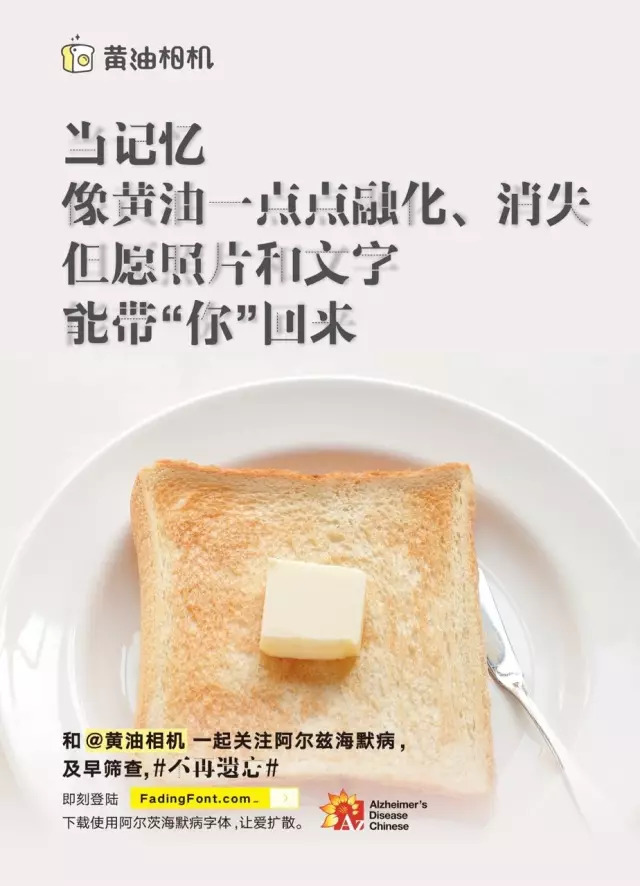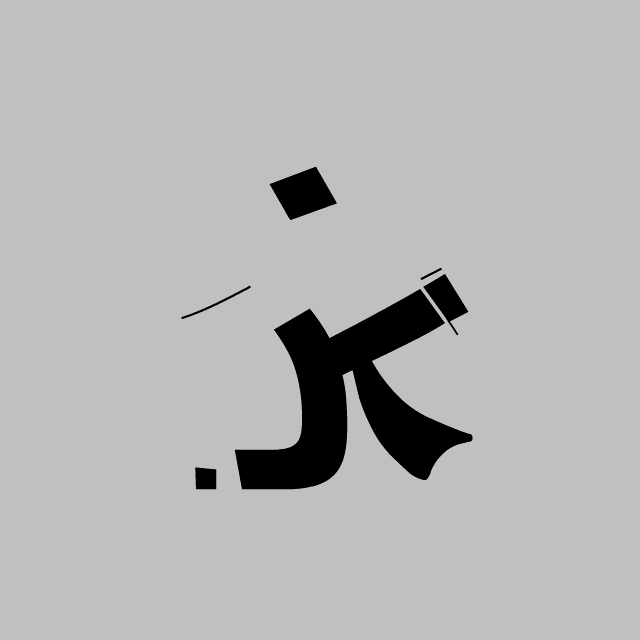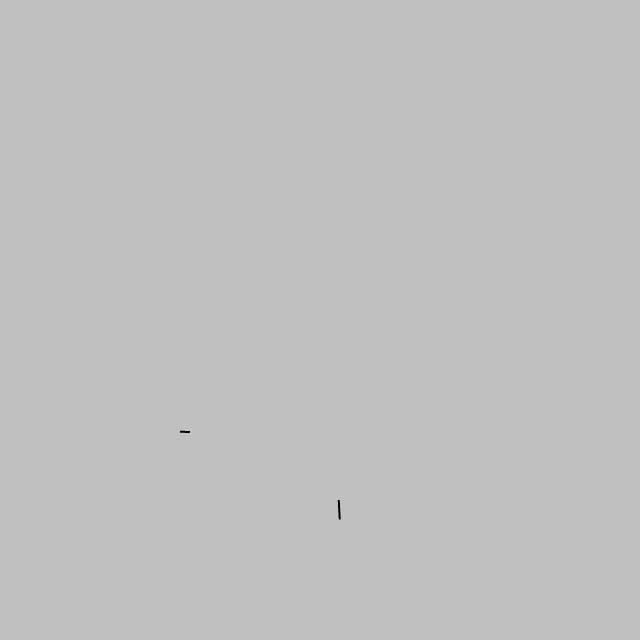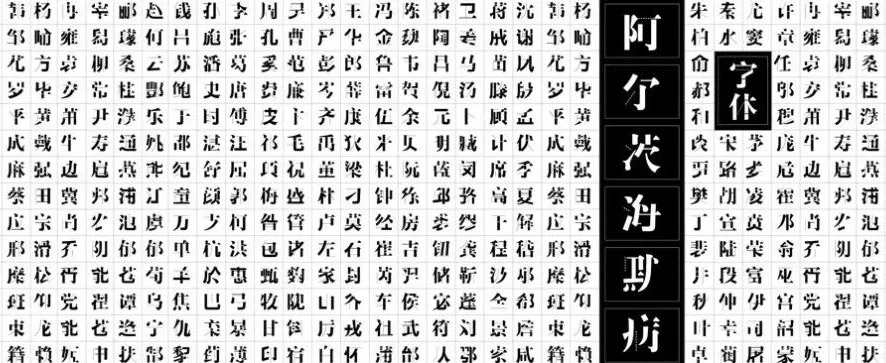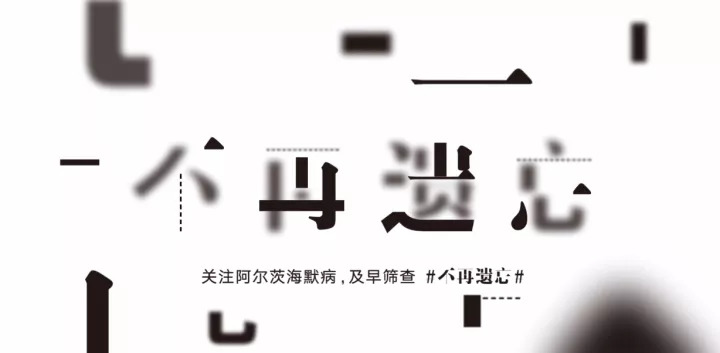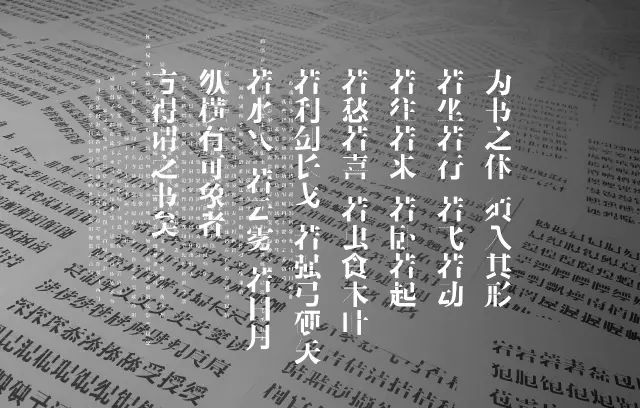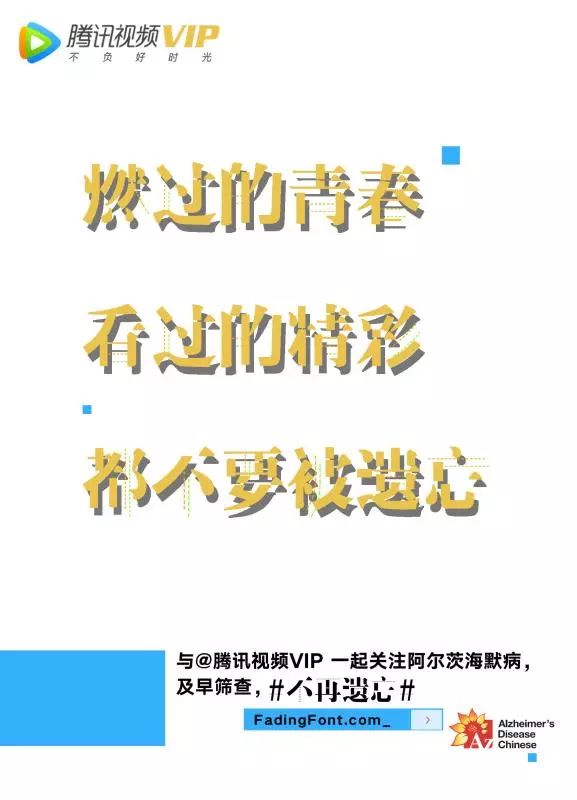
汉仪阿尔茨海默病体介绍,汉仪阿尔茨海默病体应用案例
每年9月21日都是世界阿尔茨海默病日。
字由小姐姐特别推荐一款超级有意义的字体。
一年前,围绕这一套笔画缺失的独特字体库展开了一场由中国老年保健协会老年痴呆及相关疾病专业委员会联合众多爱心企业共同发起的主题为#不再遗忘#的公益活动,推广活动希望号召公众对阿尔茨海默病的关注,促进早期筛查。
字体库的核心创意及执行团队表示:“每个人从小到大,生活方方面面都脱离不了文字。我们用文字书写情感,记载过去;它更是人和人之间,企业和公众之间,信息承载、传递的基本要素!如果患上阿尔茨海默病,认知能力和记忆力逐渐丧失,会导致忘记词汇、失去对文字的理解力,因此我们创作了阿尔茨海默病字体库。相较于单纯将字体应用于海报设计上,字体库的可延展性,开放了人们自创内容的可能。当人们看到残缺字体,就会更有同理心的关怀阿尔茨海默病患者的处境,更有主动意愿参与并支持社会公益组织提供建设性意义的帮助。”
我国阿尔茨海默病患者人数已跃居世界第一位,然而公众认知依旧不足,许多患者错过了延缓和改善病情的最佳时机。这套阿尔茨海默病字体,以缺失笔画的独特设计,直观体现了阿尔茨海默病患者认知能力减退和记忆缺失;同时,字体的缺失感设计也是希望第一时间抓住公众的眼球,进一步关注阿尔茨海默病。
这套字数庞大的字库,由汉仪字库协助制作与开发,共计近7000个文字,覆盖日常所需的常用字符,大大提高了字体的传播力。
有了这套字体作为传播载体,不仅是企业,每个普通人都能参与到这场公益行动中来,通过阿尔茨海默字体创造自己的内容,借助自己的社交平台分享,引起更多人对阿尔茨海默病的关注,促进早期筛查。
《#不再遗忘#世界阿尔茨海默病日公益倡导》得到了社会多方面的认可,近一年来分别荣获了,2018年戛纳国际创意节health&wellness类别银狮子;2018亚太广告节Integrated Lotus金奖;2017年第八届金鼠标国际数字营销节公益营销类全场大奖、金奖、最佳创意表现奖、全场最佳人气奖等诸多荣誉。
与字同行,不再遗忘,
我们用文字创意将爱点亮中国,点亮世界!